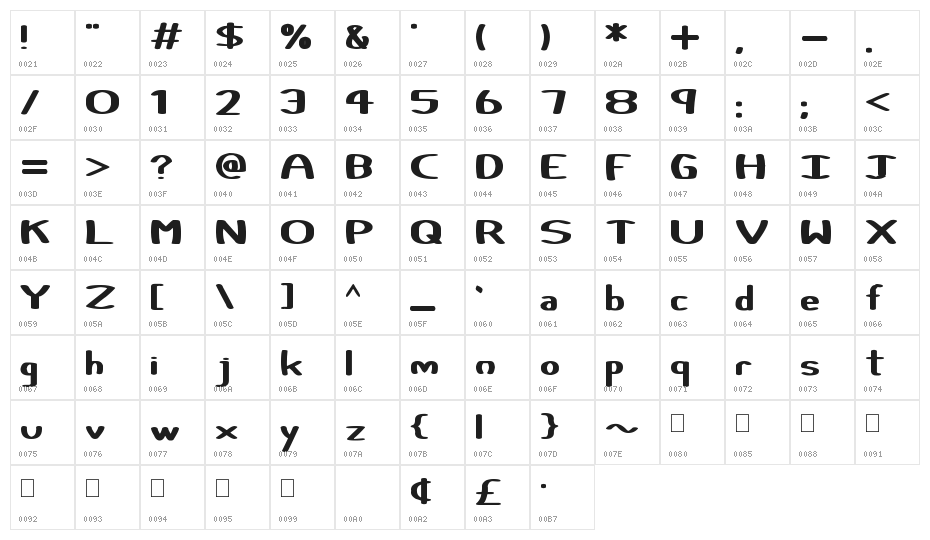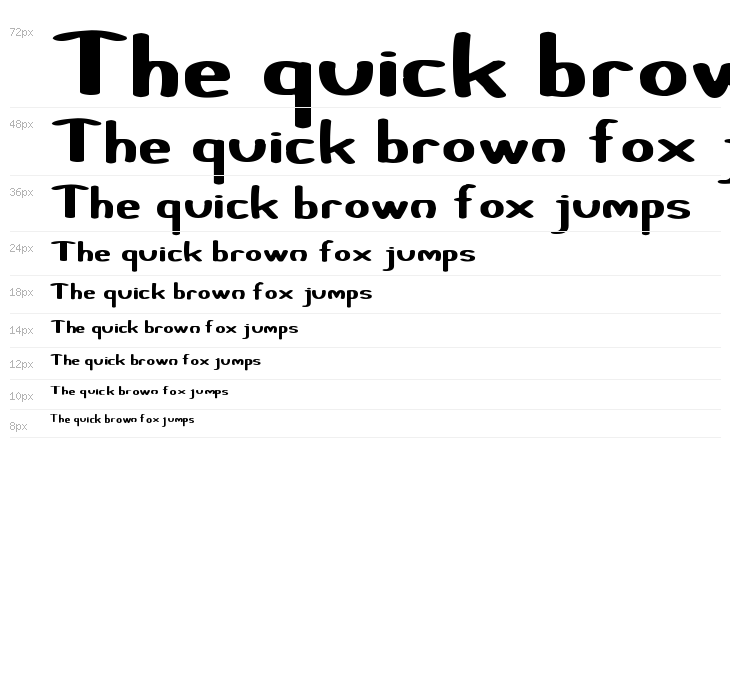
Certainly Font
| समग्र शैली | Playful, Hand-drawn |
| उपयोग का मामला | Headlines, Logos, Posters |
| सुझाए गए प्रोजेक्ट | Ideal for children's books, playful branding, posters, and creative invitations. |